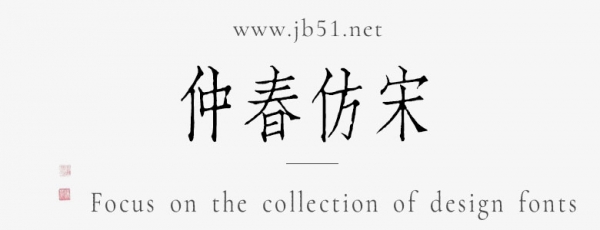
仲春仿宋是一款不錯的藝術(shù)字體,,字體筆觸略細,具有很好的視覺感,適合應(yīng)用于藝術(shù)設(shè)計、平面宣傳設(shè)計、網(wǎng)頁設(shè)計,書法字帖等領(lǐng)域,需要的朋友可以前來本站下載。
「仲春仿宋」項目是對上世紀(jì)聚珍仿宋二號長體鉛活字字形進行的數(shù)字化。采用直接復(fù)刻辦法,從印刷品掃描件中提取字形并封裝為字體。